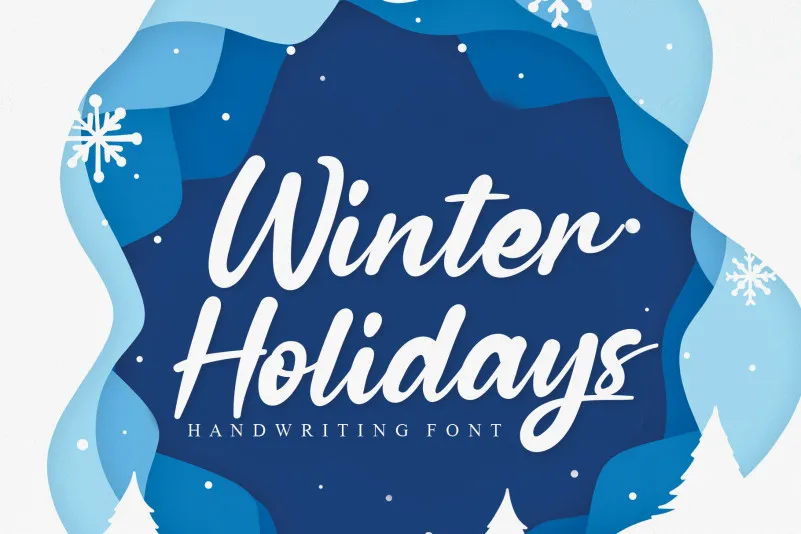
Winter Holidays Script Font – Download Grátis
A fonte ‘Winter Holidays Script Font’ é uma escolha ideal para designers buscando adicionar um toque único e emocional a seus projetos. Desenhada pelo designer andikastudio, ela traz características fluidas e robustas que combinam perfeitamente com o tema das festividades de inverno. Seus traços leves e sua estilização elegante fazem dela uma fonte elegante para usar em cartões de aniversário, mensagens pessoais e qualquer outra publicação especial durante os feriados de inverno. Este é um ótimo exemplo de como a mão escrevendo pode transformar simples textos em experiências memoráveis. Se você está procurando por uma fonte que transmita um sentimento de festividade, leveza e serenidade durante esta estação do ano, não hesite em experimentar ‘Winter Holidays Script Font’.